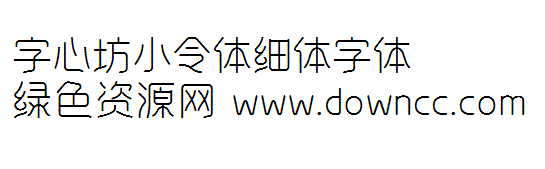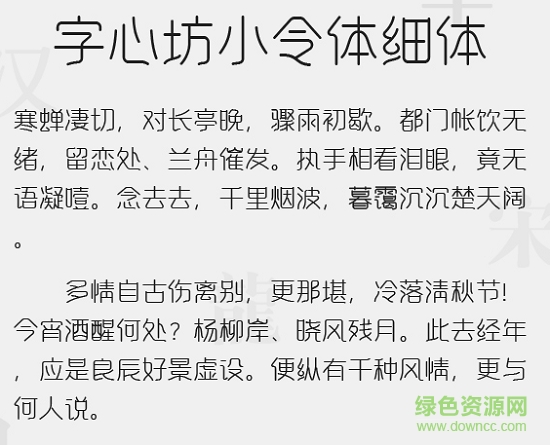
字心坊小令體細(xì)體字體是一款字心坊類耐看型字體軟件,中細(xì)體以簡(jiǎn)約細(xì)膩的筆畫,給人非常有活力的感覺,工整有勁,整體效果大方得體,感興趣的朋友歡迎來綠色資源網(wǎng)下載體驗(yàn)!
字心坊小令體是一款中文細(xì)體。由于顯示硬件更新?lián)Q代,顯示像素增大,對(duì)字體的細(xì)節(jié)處要求極高。中細(xì)體在遵循傳統(tǒng)黑體的一般特點(diǎn)上加入更多新元素,筆畫與字形比例加大,字體重心在同一軸線上,增強(qiáng)了易讀性。字心坊小令體,筆畫與字形比例小于1:20,筆畫更加纖細(xì),在高分辨率顯示屏幕上顯示質(zhì)感非常好;結(jié)構(gòu)重心在同一軸線上,整個(gè)字方正重心微上,生機(jī)勃勃;字間距隨著筆畫和字形比例變小也做了相應(yīng)的調(diào)整,整體讀來字字珠璣又一脈相承。
經(jīng)小編測(cè)試使用,字心坊小令體在電腦端打字聊天受到非常多書友們的贊美,這款字體非常好看,細(xì)膩文雅,拿來裝逼再合適不過了!